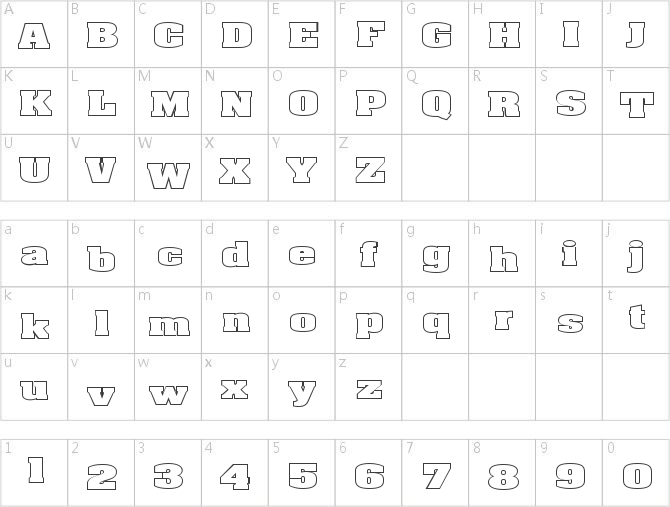
FZ BASIC 52 HOLLOW EX 詳情頁(yè)
FZ BASIC 52 HOLLOW EX字體字庫(kù)是一款讓人賞心悅目、百看不厭的英文字體,適合各類(lèi)廣告和產(chǎn)品包裝設(shè)計(jì)應(yīng)用,字體大小0.09MB,格式為ttf字體,上傳用戶是ㄚòひ慬偶鰢,作者/版權(quán)方為未知